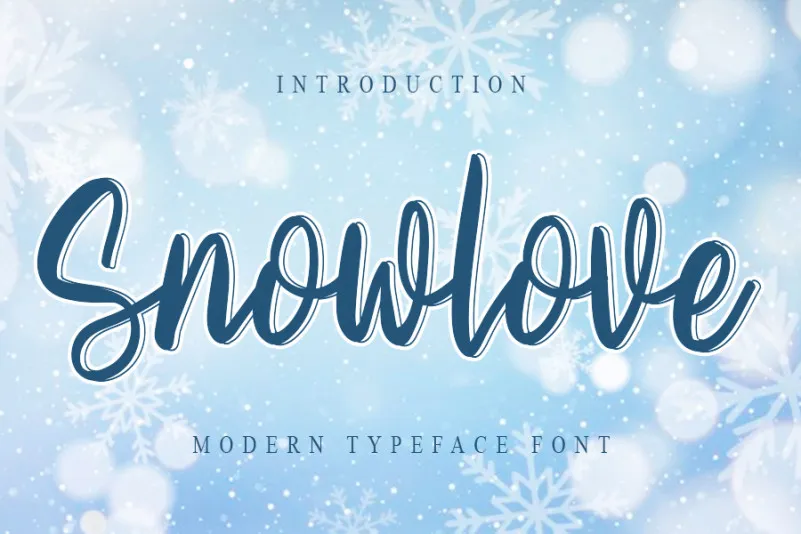
Snowlove Script Font – Download Grátis
A Snowlove Script Font é uma elegante fónta escrita à mão que combina elementos relaxados com beleza poética. Escrevida à mão livre e rica em detalhes, esta fonte retrata um estilo delicado de pintura, perfeita para diversos usos criativos. Perfeita tanto para logotipos quanto para cartões de casamento, o design delicado da Snowlove Script é ideal para cabeçalhos, camisetas personalizadas, letras de porta-moeda, sinalização, etiquetas, notícias, panfletos e até mesmo adesivos. Suas linhas suaves e suas formas desenhadas pelo designer freshtypeink criam um design único que se adapta à uma variedade de tamanhos e contextos de uso. É uma escolha perfeita para os designers que buscam uma fonte de escrita à mão única capaz de brilhar em qualquer aplicação visual, tornando o processo de criação mais gratificante e inspirador.